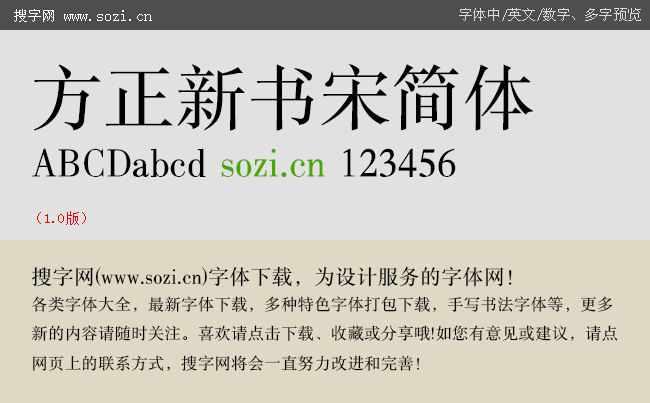
方正新書宋簡體(FZXSSJW)
搜字網(wǎng)提供一款方正新書宋簡體中文字體下載,方正新書宋簡體是一款字形清秀的中文字體,該字體結(jié)構(gòu)優(yōu)美,識別性好,常用于產(chǎn)品設(shè)計、包裝印刷、報刊雜志、正文標(biāo)題、繪畫創(chuàng)作等廣告設(shè)計場合使用。